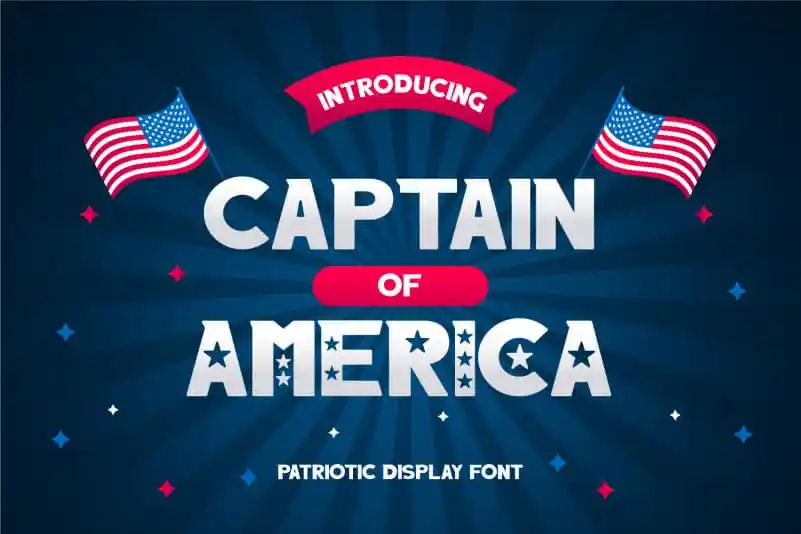
Captain of America Font – Download Grátis
A Captain of America Font é uma fonte para uso no estilo sans serif que traz consigo a essência do espírito patriótico de forma única e vibrante. Esta fonte destaca-se não apenas pelo seu formato minimalista, mas também pela sua natureza festiva e imbuída de coragem, ideal para aqueles projetos que buscam um toque especial de energia e vitalidade. Com o Designer Heloyud como criador, a fonte é uma escolha perfeita para designers e estilistas em busca de uma opção visual moderna e versátil que traga um ar de força ao seu trabalho. Seja para gráficos digitais, logotipos ou qualquer projeto de design onde você precisa de uma fonte robusta e colorida, a Captain of America Font é o elemento ideal para criar uma impressionante identidade visual.
Designer: Heloyud